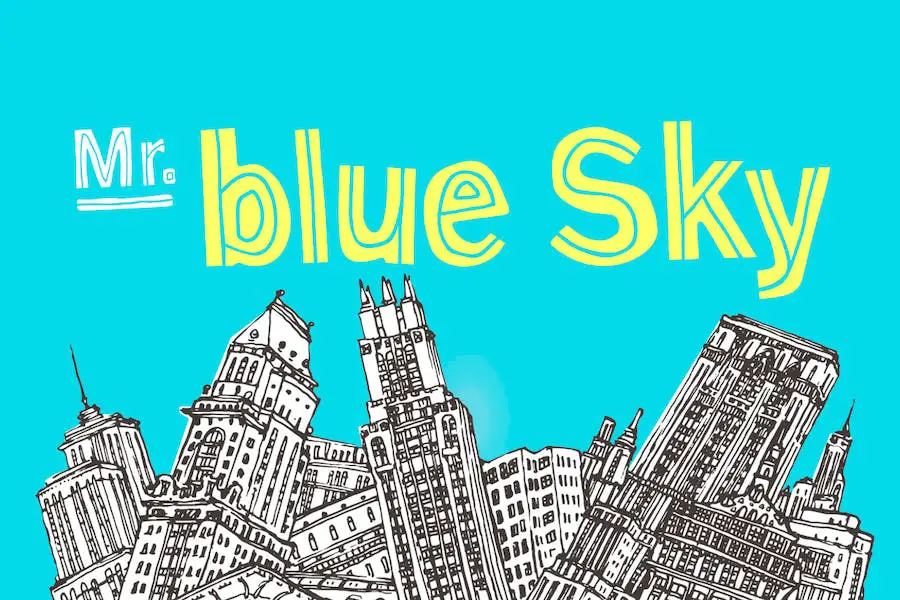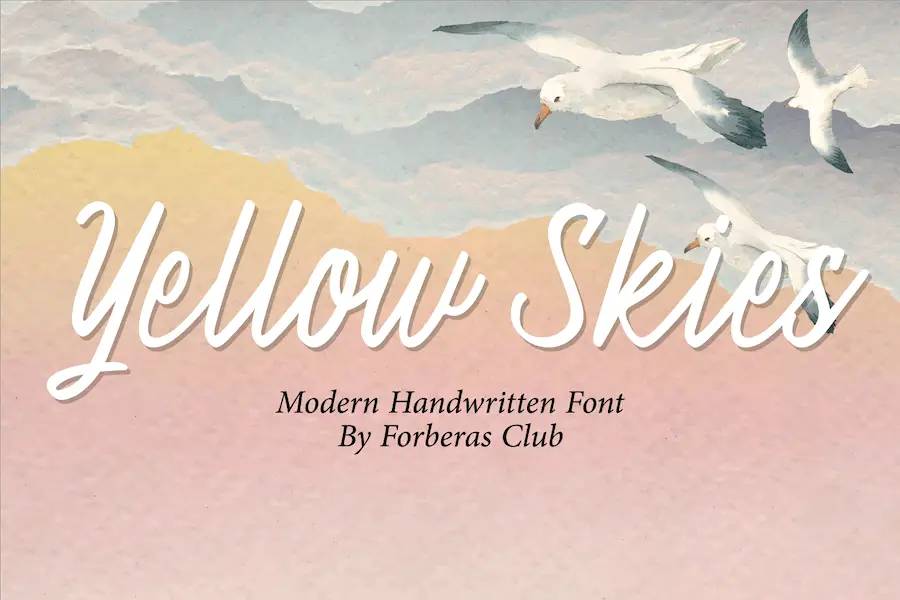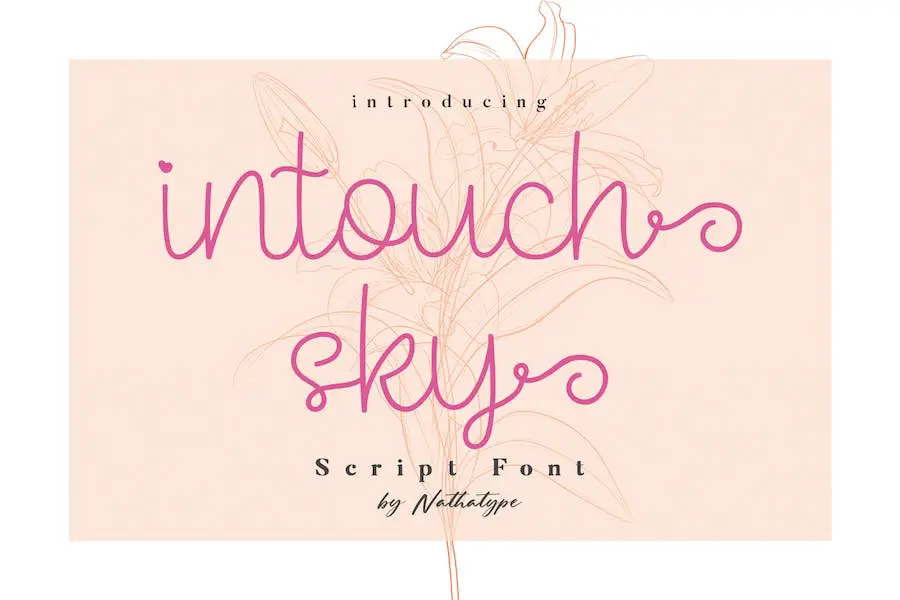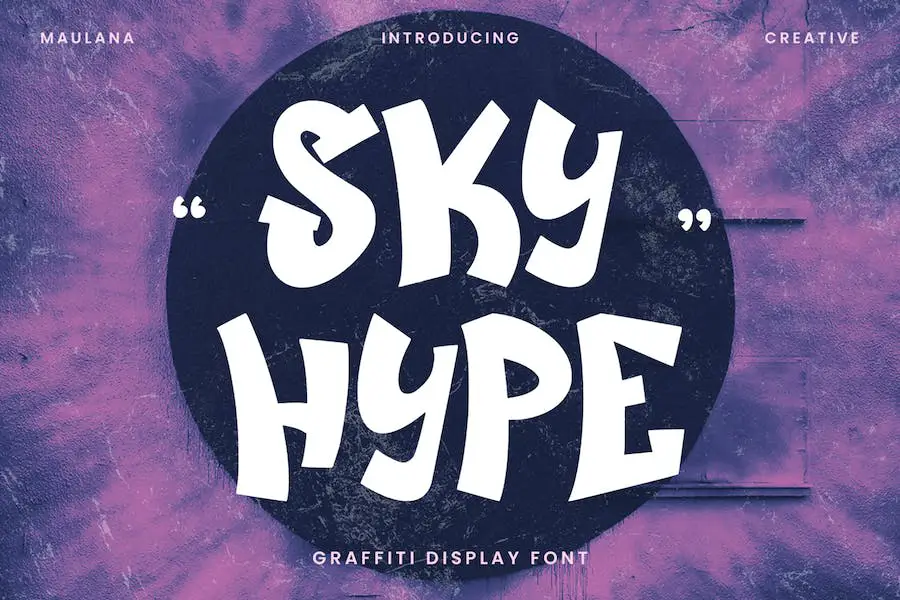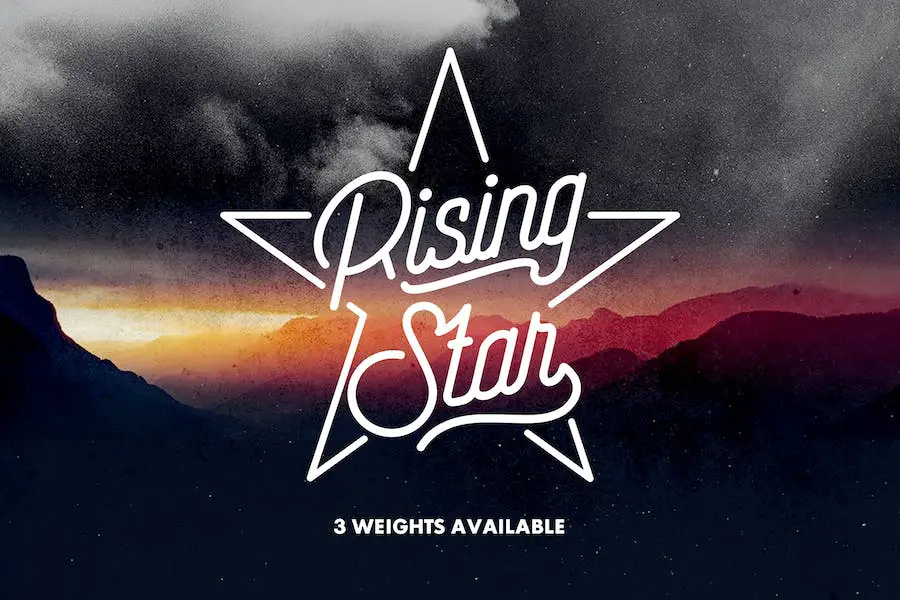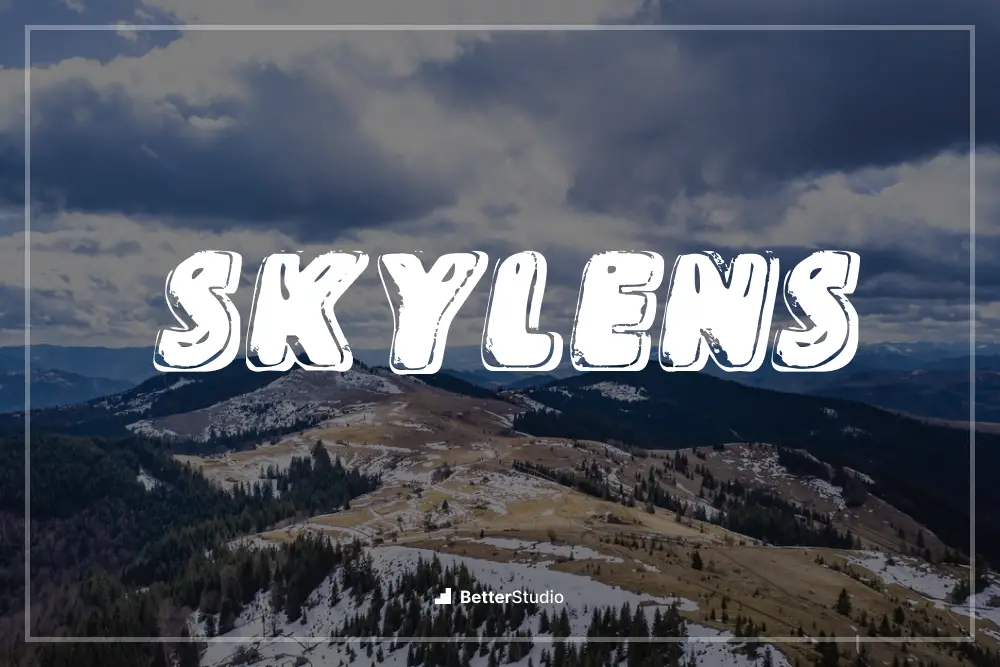
15 meilleures polices Sky 2023 (gratuites et premium)
Publié: 2023-09-20Êtes-vous un graphiste à la recherche de la police parfaite pour rehausser vos projets ? Ne cherchez pas plus loin que notre liste des 15 meilleures polices Sky de 2023, options gratuites et premium.
Les polices Sky peuvent ajouter une touche de magie et de créativité à vos créations, et nous avons organisé une collection qui inspirera certainement votre prochain projet.
Maintenant, vous vous demandez peut-être ce qui rend ces polices les meilleures ? Eh bien, nous avons fait nos recherches et sélectionné les meilleures polices Sky en fonction de leur popularité, de leur polyvalence et de leur attrait esthétique.
Avec ces polices, vous pouvez apporter une touche d'émerveillement et de beauté à vos créations, qu'il s'agisse d'un site Web, d'un logo ou de supports de marque.
Dans cet article, nous explorerons les 15 meilleures polices Sky de 2023, en présentant leurs caractéristiques, styles et applications potentielles uniques.
Des polices avec empattement élégantes et vaporeuses aux options sans empattement audacieuses et modernes, il y en a pour tous les besoins en matière de conception. Alors attachez votre ceinture et préparez-vous à vous envoler à travers les nuages avec ces superbes polices inspirées du ciel.
Meilleures polices Sky Premium
Présentation de la collection exquise de polices Sky haut de gamme qui propulseront vos créations vers de nouveaux sommets.
Explorez ces polices captivantes qui évoquent la beauté et la sérénité du ciel et élevez vos projets à un tout autre niveau.
Plongez et découvrez la police parfaite qui apportera une touche d'élégance éthérée à vos créations.
Ciel glacial
Frosty Sky est une police polyvalente qui offre un style brossé à la main et un support multilingue. Il est parfait pour un large éventail de projets artistiques, notamment des t-shirts, des magazines, des couvertures de téléphone, des publications sur les réseaux sociaux, des menus de restaurant, des cartes de vœux, des invitations, des mariages, des en-têtes et bien plus encore.
Avec Frosty Sky, vous aurez accès aux caractères minuscules et majuscules, ainsi qu'aux caractères alternatifs, à une sélection généreuse de signes de ponctuation, de ligatures, de chiffres et à la prise en charge de plusieurs langues.
Ce duo de polices offre tout ce dont vous avez besoin pour mettre en valeur vos créations et leur donner une touche unique et artistique.
Ciel bleu
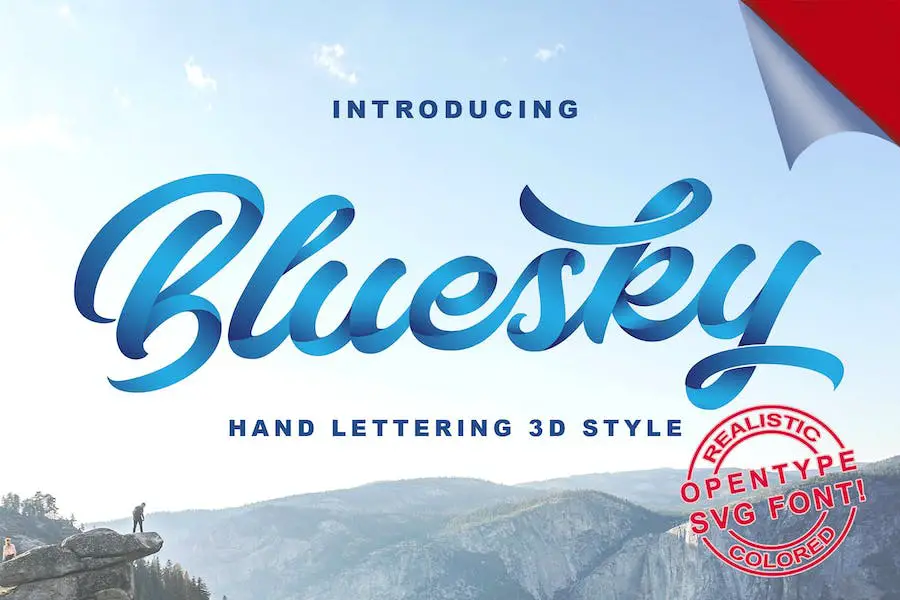
Bluesky est un script de police unique qui ajoute de la profondeur et de la dimension à vos créations. Avec ses détails d'ombre, il crée un effet 3D époustouflant qui élèvera vos projets au niveau supérieur.
Cette police comprend des majuscules, des minuscules, des chiffres, de la ponctuation, des caractères alternatifs et des caractères multilingues, offrant une polyvalence pour divers besoins de conception.
Ce qui distingue Bluesky, c'est sa couleur bleue personnalisable. Bien qu'il soit livré avec une teinte bleue de base, vous avez la liberté de changer la couleur en fonction de vos préférences.
Craqueur du ciel
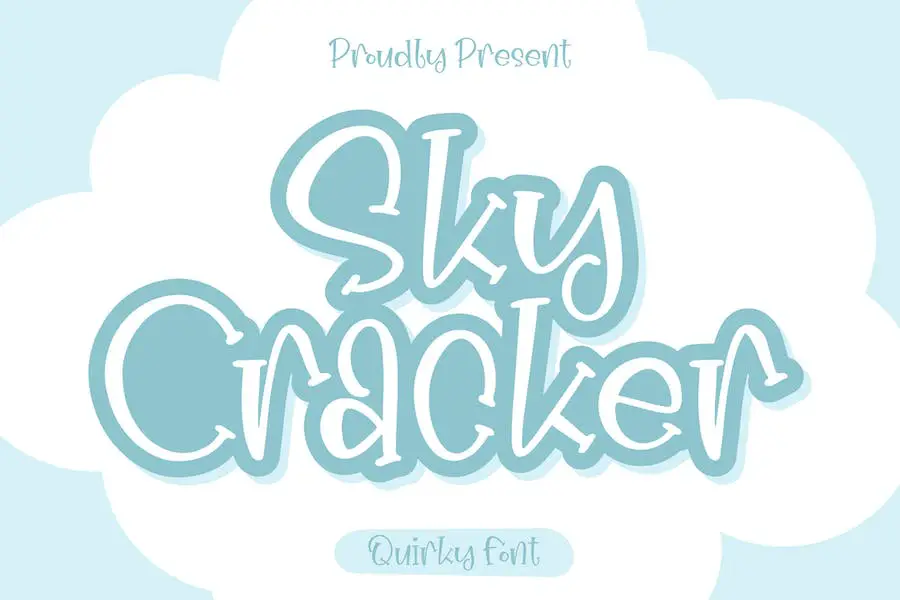
Sky Cracker est une police époustouflante qui propulsera vos projets de conception vers de nouveaux sommets. Cette magnifique police de caractères est le complément parfait à votre collection, que vous soyez graphiste ou simplement un créatif cherchant à améliorer vos créations numériques et imprimées.
Avec son style élégant et polyvalent, Sky Cracker est idéal pour un large éventail d'applications, des affiches accrocheuses aux publications captivantes sur les réseaux sociaux.
Ses lignes épurées et son esthétique moderne en font un excellent choix pour les projets de marque, tout en ajoutant une touche personnelle à toute entreprise. Avec Sky Cracker, les possibilités sont infinies. Alors pourquoi attendre ? Plongez dans le ciel nocturne et laissez votre créativité s'envoler avec cette police incroyable.
Histoire Ciel
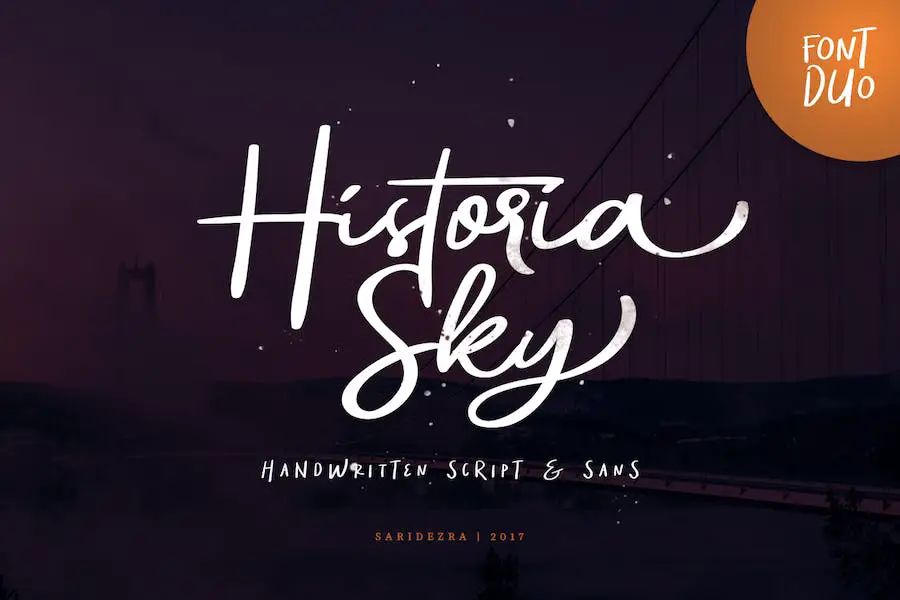
Historia Sky est un duo de polices manuscrites polyvalent qui offre une gamme d'options créatives. Avec ses alternatives et ses swashes élégants, vous pouvez personnaliser votre propre signature unique ou créer d'adorables citations.
La police prend également en charge plusieurs langues, la rendant accessible à un public plus large. Il est disponible aux formats OTF et TTF, garantissant la compatibilité avec divers logiciels de conception.
De plus, Historia Sky prend en charge PUA, ce qui vous permet d'accéder facilement à des personnages supplémentaires. Que vous travailliez sur un projet personnel ou sur un design professionnel, cette police offre des possibilités infinies. Donnez une touche personnelle à vos créations et laissez libre cours à votre imagination avec Historia Sky.
Ciel doux
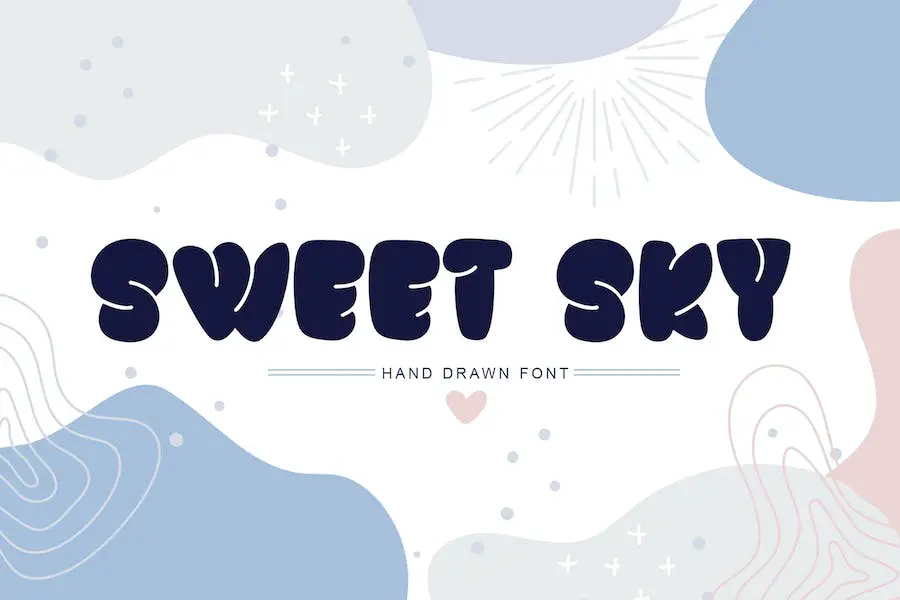
Présentation de Sweet Sky ! Cette police unique faite à la main est le complément parfait à votre boîte à outils de conception. Avec son style d'affichage mignon et moderne, il fera ressortir vos projets. It Rotund Font est une police qui captivera votre cœur dès la première utilisation.